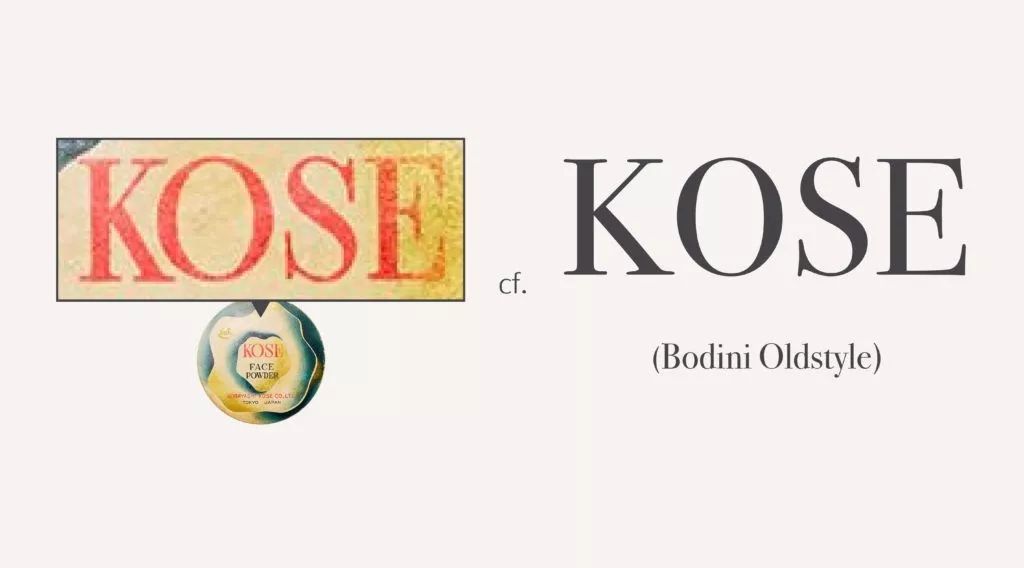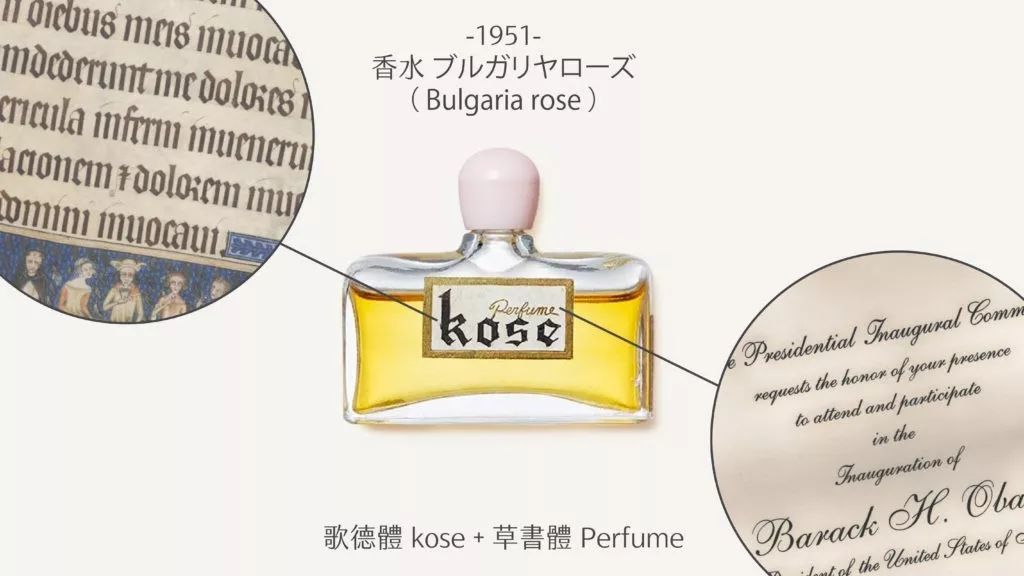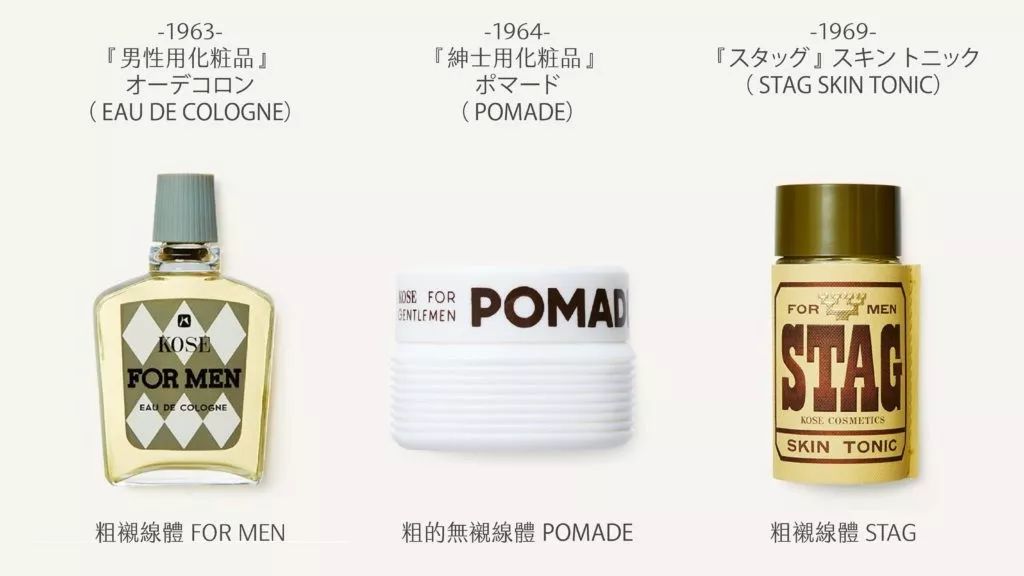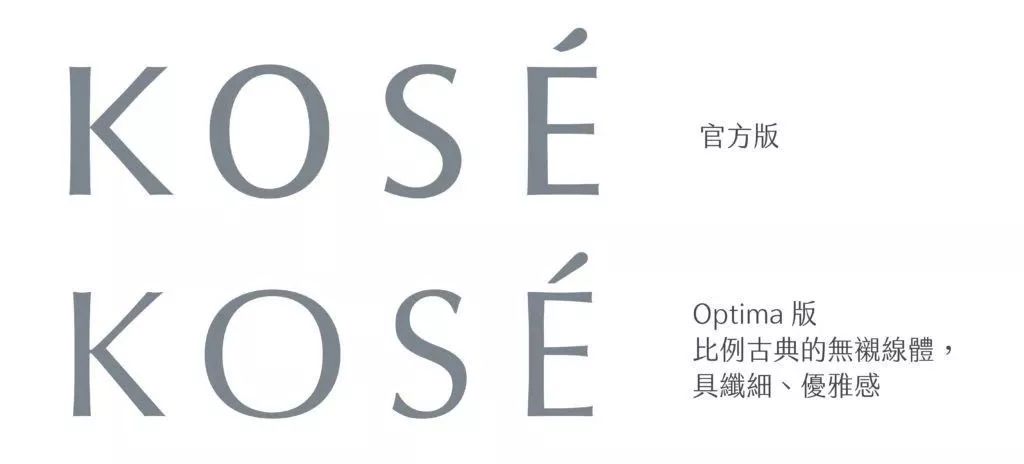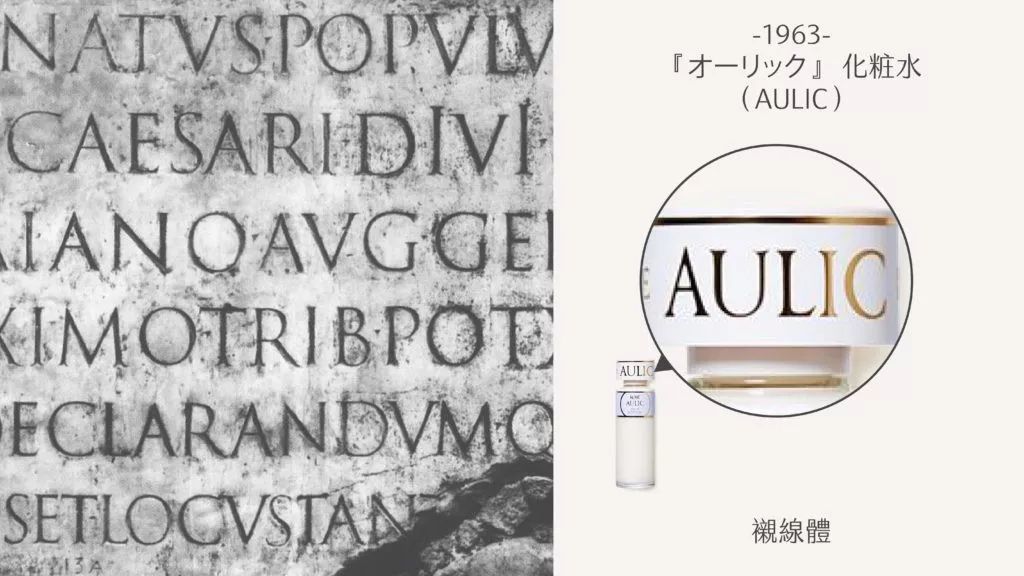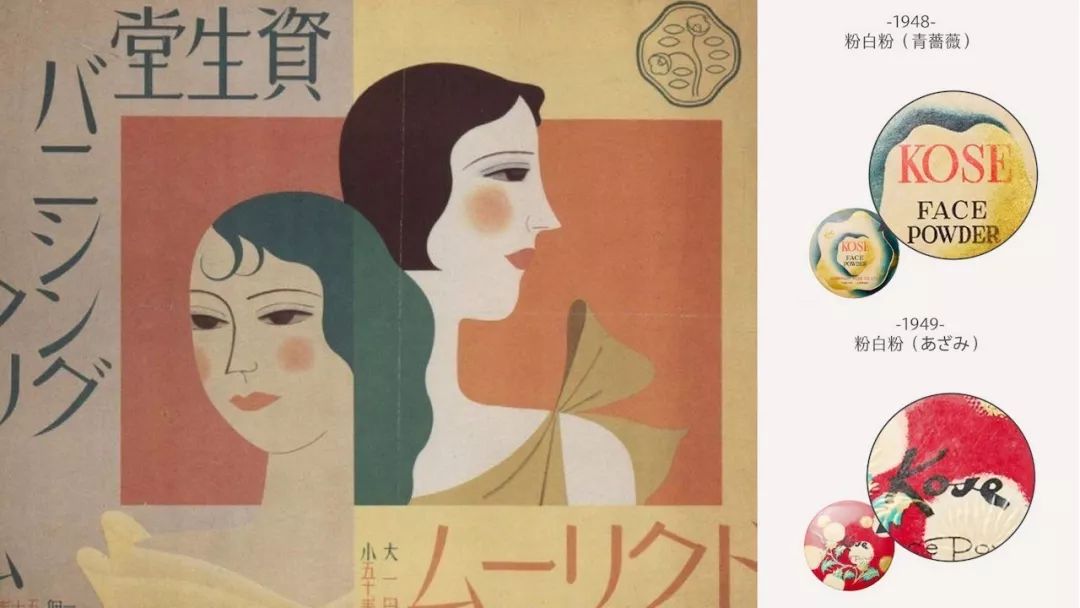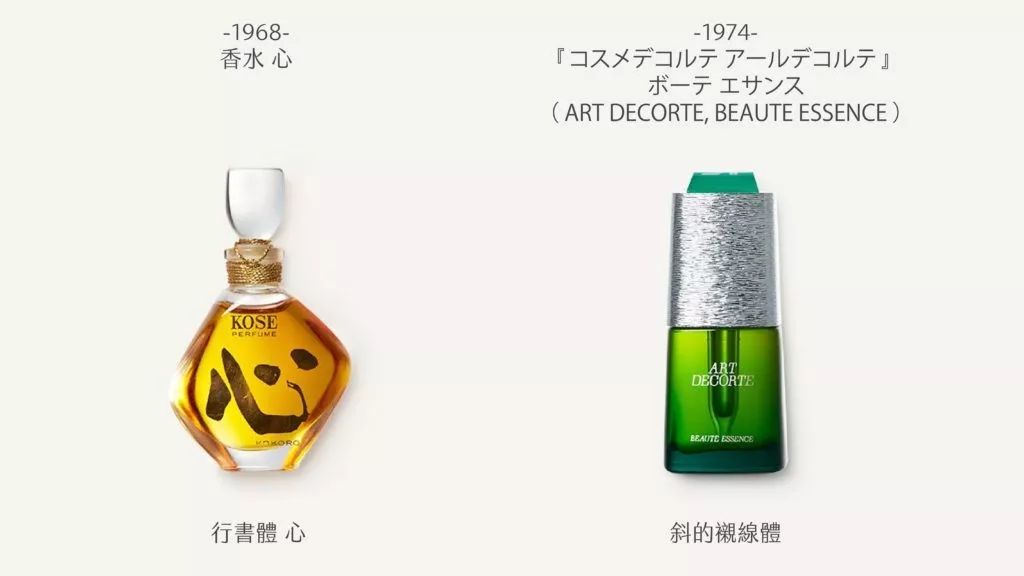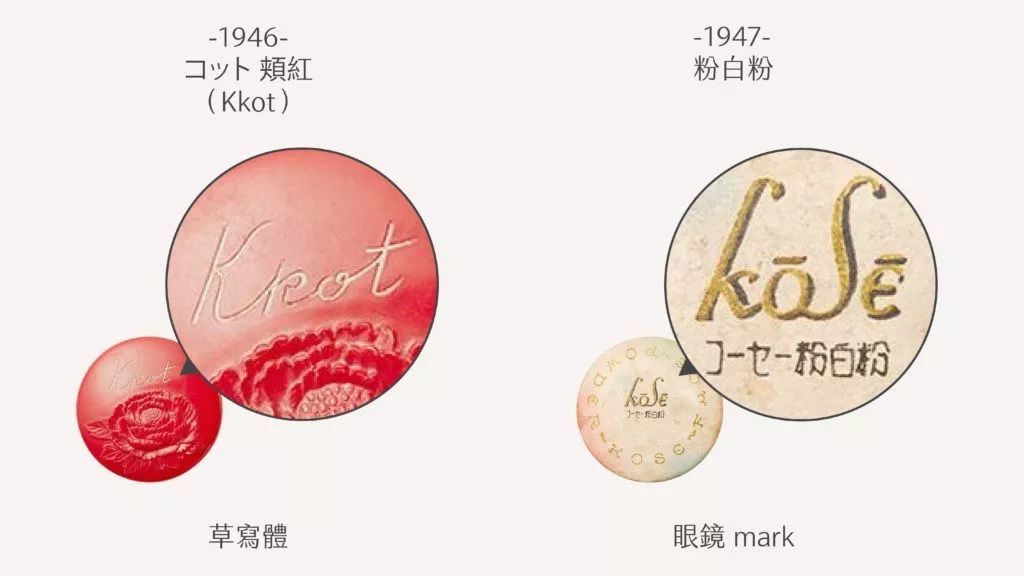
资生堂的这些套路,你看懂了吗?
打广告有许多途径,美女营销更是一种由来已久的销售手段。而对于化妆品厂商来说,美女可不能只是营销代名词,它更是个必须被善用的文化符号。而带着深厚文化底蕴的字体跟人体结合、造型堪比容貌,是否再次打开一个灵感大门?
资生堂的字体设计
要透过字体设计做出美女形象,并不是件容易的事情。经典化妆品字体案例:资生堂。资生堂书体造型优美,是相当鲜明的企业识别设计。它始于 1916 年资生堂创办设计部之后,资生堂同时也向新人与外界表达他们对美的执着。
但事实上,资生堂也是耗费了不少心力,才设计出如此优美的字体。视觉中心逐年提高,中间的口字逐渐增大。
这种变化有如人体骨架的改变。前期头重脚轻,就好像女孩的身体比例;中间是成长中的少女,身体稍微抽高,但还不太稳固;后期则是二十多岁的妙龄女子,头身比例近于模特儿,也能挺然、自信迎接身体的改变了。
1927 年的冷霜以及雪花膏广告中,“资生堂”的品牌识别已相当鲜明。
至于英文“SHISEIDO” 的字体设计,则反映出欧陆的艺术潮流。新艺术运动以充满活力、波浪形和流动感作为风格特征,故经常用花卉等植物作为设计母题。
当时资生堂的董事长福原信三受到启发,他以女性秀发中的美丽花朵为灵感,创作出山茶花形象的标志。
这似乎也影响到LOGO中“S”的设计,S就像女性柔顺的长发,以充满流动感的曲线呼应新艺术运动。
KOSE的字体设计
就和其他化妆品牌一样,KOSE也致力于求取美感。1946年草创之初,KOSE以手写感草体作为企业识别面世。
1948年o、e上面的横取消了,“KOSE”四字改用下方弧线串连。
有趣的是,这时他们似乎努力地探索LOGO风格,右侧的青蔷薇粉白粉中可见三个“KOSE”,中央是鲜明的红字衬线体,下方有红字无衬线体的公司全称。
衬线是依附于笔画起收端点的细线,由于古罗马石刻的大写字母中已可见到此特征,因此衬线体又被称作罗马体。
此类的字型相当多,“KOSE”的设计类似缩过字间距离的Bodini Oldstyle字型,在优雅之余富含简洁感,正能贴合干练、明快的女性上班族形象。
时至 1951 年,LOGO风格变化尚未停歇,如保加利亚玫瑰香水就是个很有趣的例子。
“kose”粗细对比极强、字字分离又转折尖锐,竟与线条细瘦连绵、且转折圆润的草写“Perfume”相互搭配,视觉效果颇为冲突。
歌德体是流行于 12 到 17 世纪西欧手抄书的字体风格,特色是以夸张的造型诠释华丽感,常见于圣经之中。
草书体则是 18、19 世纪英国上流阶级手写书信的常见风格,其高雅、名贵的形象,让它成为今日西洋贺卡、邀请函上的主角。KOSE 之所以如此设计,或许是想传达玫瑰神圣且浪漫的双重形象吧!
1963 年宫廷AULIC乳液上的字体,则带我们进入另个世界。“AULIC”采用Trajan系列的Goudy Trajan字型。
这款字的风格源自古罗马帝国皇帝图拉真凯旋柱上的碑文,造型细节相当丰富,它的字母较为窄长,装饰线微微内凹且曲度优美,因而予人高贵、精致的感受。
历经了不同的 logo 尝试,KOSE 近期停留在无衬线体。这款设计近于 Optima 字型,由于结构与比例相当古典,明明去除了衬线,却能带给人如衬线体般的纤细、雅致印象,因而能维持住先前 logo 的罗马感。
这种转变也符合时尚潮流,随着视觉载体从印刷品转向荧幕,近年来时尚品牌如 CHANEL、ESTĒE LAUDER、SHISEIDO,纷纷转用无衬线体。
当化妆品牌遇上男性
如今化妆品早已不是女性的专利,该如何让消费者在面对琳琅满目的化妆品时,能快速识别出男性专用的品项呢?这得思考男性的视觉习惯才行。
20世纪50年代左右特别流行以美国西部开拓时代为背景,主打牛仔、枪手等阳刚男性形象的西部片,一直是经典且深受男性喜爱的电影类型。其电影海报经常采用特定字体类型就是“粗衬线体”。
顾名思义,粗衬线体的特征就是加粗、加厚的衬线设计。原先依附在笔画起收端点的细微衬线,因而变成颇具量感的块状造型。
粗衬线体起源于19世纪初期的欧洲,因为设计相当大胆且引人注目,所以常被广告商用于海报设计。Mac内建的Courie以及Rockwell 字型,都是著名的字型范例。
KOSE似乎也注意到了粗衬线体与男性的强烈连结。
1959年的男性用古龙水,即以大且粗的粗衬线体写上“FOR MEN”。衬托字体的底面设计也很有趣,大地色系的菱格纹造型,不禁令人想起穿上菱格纹背心的欧陆绅士,简练也是KOSE用于男性化妆品的设计思维。
1964年的男士发蜡,在色调、造型、字体上,都是简洁的设计。
这种男性意象的强调,在1969年的男士化妆水(STAG)又更加深化。STAG 是成年雄鹿的意思,KOSE以粗衬线体写出STAG一词,并放了鹿角的图像,营造雄强、威武形象的企图不言而喻。